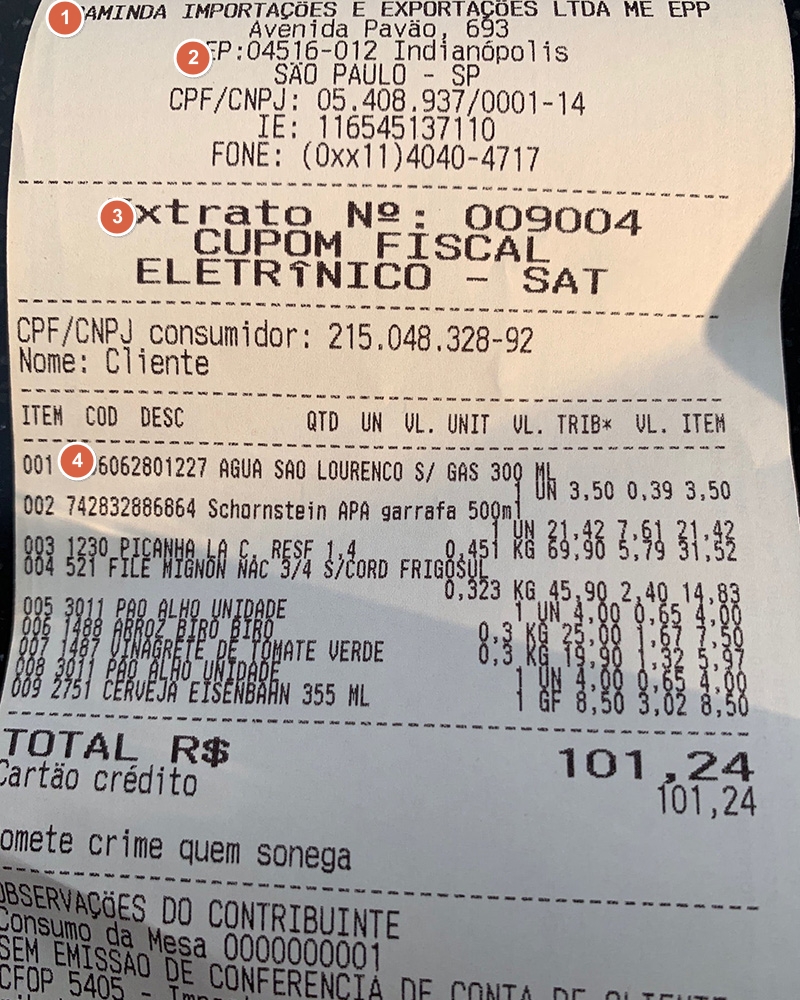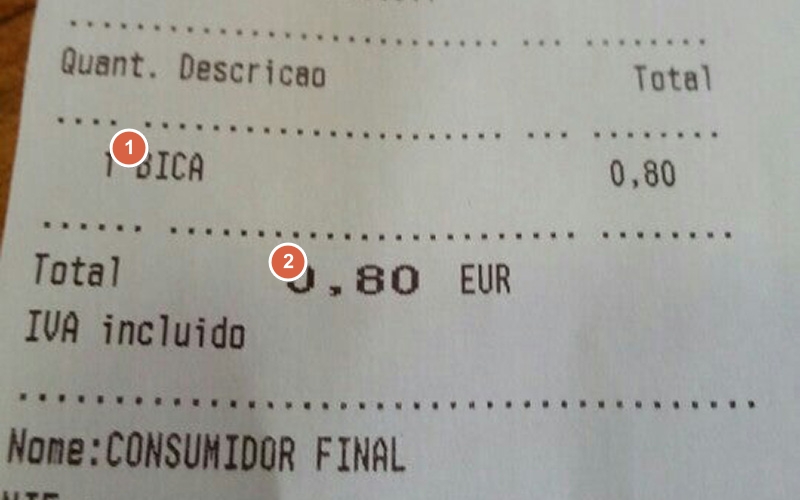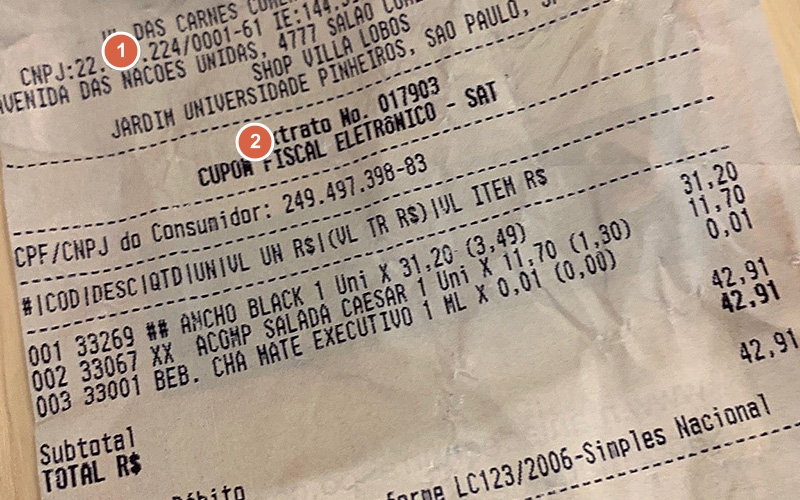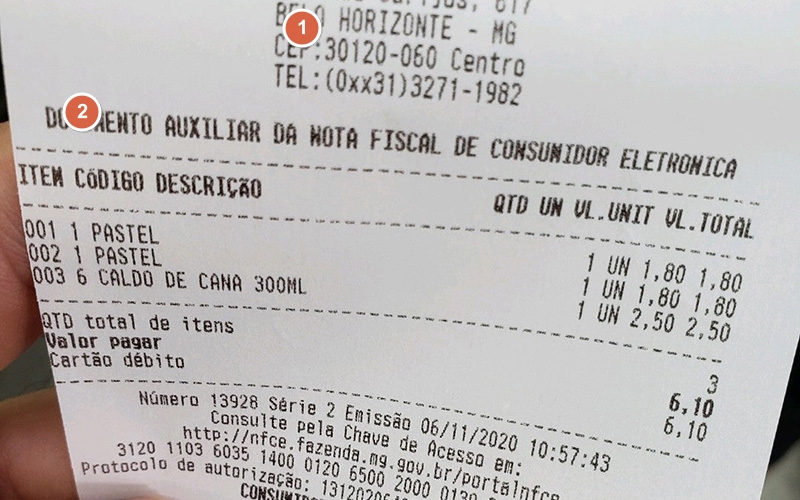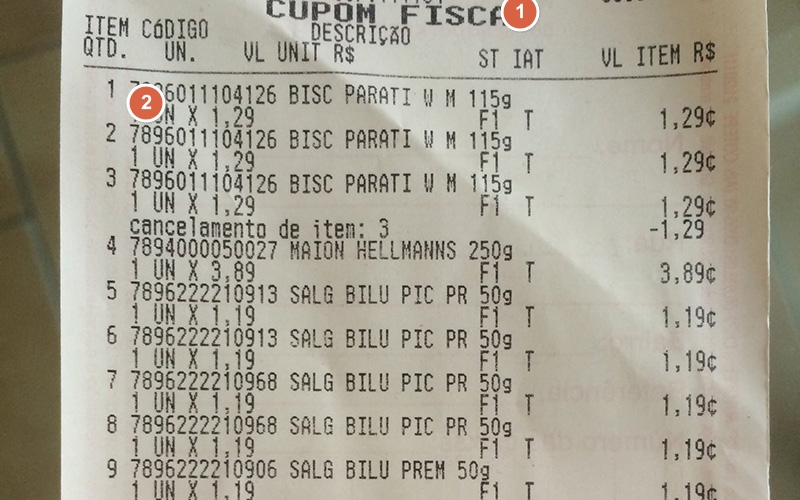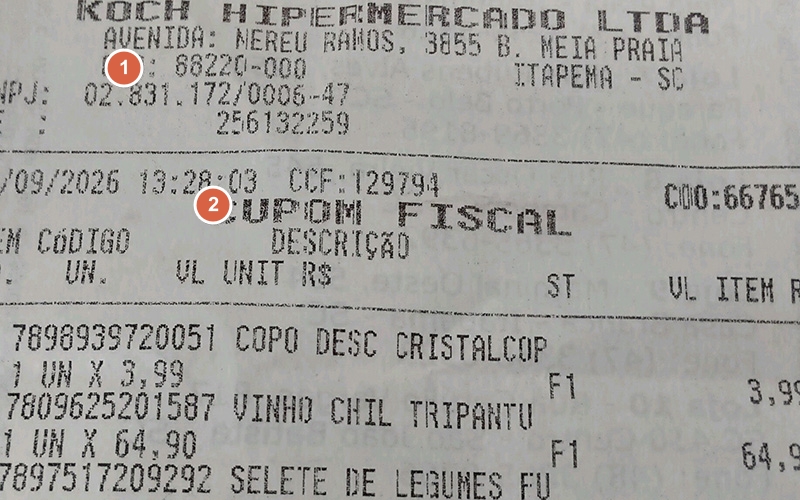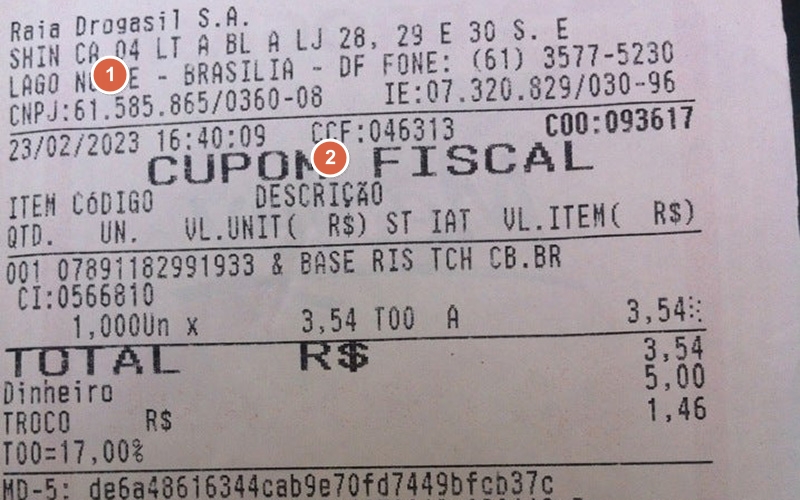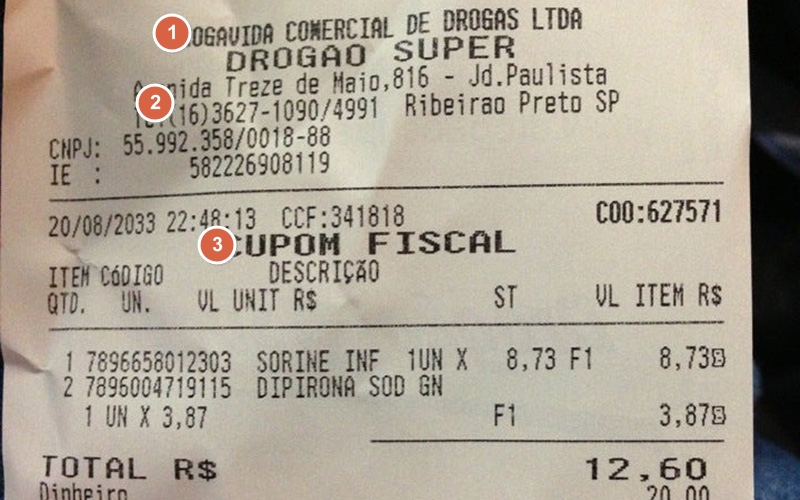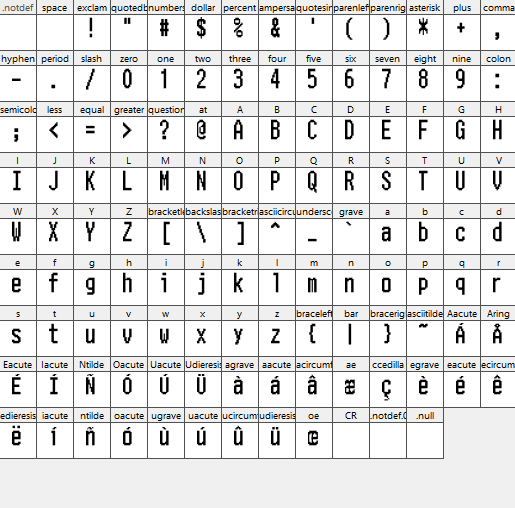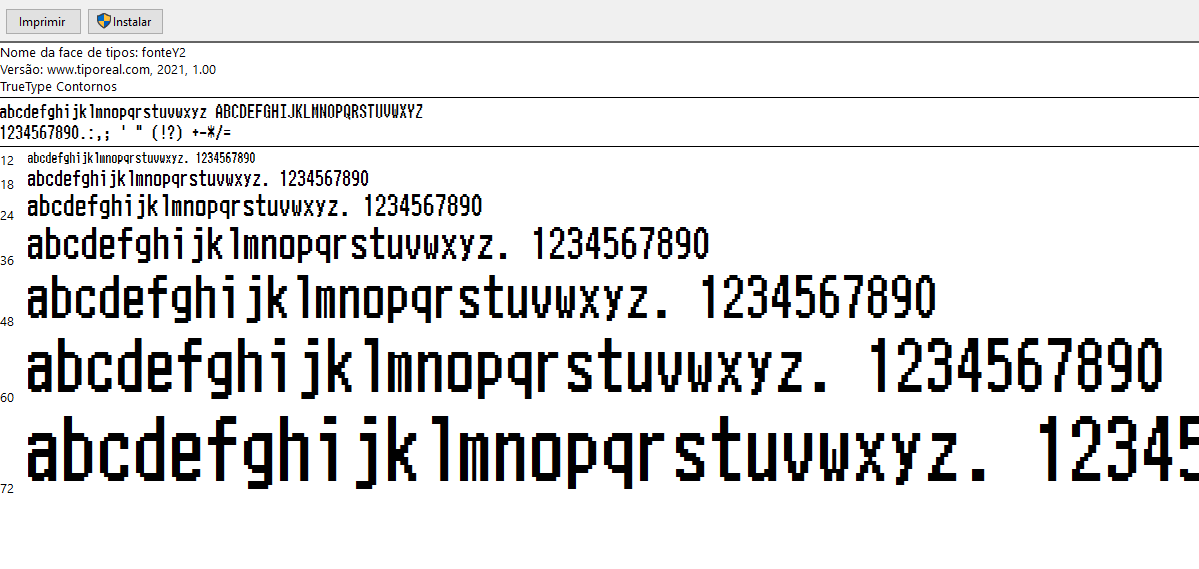
Amostra impressa da fonteY2 para nota fiscal de um restaurante em Brasil⤴
Amostra impressa da fonte para nota fiscal de um farmácia em Brasil⤴
Amostra impressa da fonte para cupom fiscal de um restaurante em Brasil (❶fonteZ2-negrito ❷fonteZ2 ❸fonteZ2-largo ❹fonteY2)⤴
Amostra impressa da fonte para nota fiscal de um restaurante em Brasil (❶fonteY2 ❷fonteZ2-negrito ❸fonteZ2)⤴
Amostra impressa da fonte para conta de um restaurante em Portugal (❶fonteY2 ❷fonteY2-largo)⤴
Amostra impressa da fonte para cupom fiscal de um restaurante em Brasil (❶fonteY2 ❷fonteY2-negrito)⤴
Amostra impressa da fonte para nota fiscal de um pastelaria em Brasil (❶fonteY2 ❷fonteY2-negrito)⤴
Amostra impressa da fonte para cupom fiscal de um supermercado em Brasil (❶fonteY2-negrito ❷fonteY2 ❸fonteY2-largo)⤴
Amostra impressa da fonte para cupom fiscal de um hipermercado em Brasil (❶fonteY2-largo ❷fonteY2)⤴
Amostra impressa da fonte para cupom fiscal de KOCH hipermercado em Brasil (❶fonteY2 ❷fonteY2-largo)⤴
Amostra impressa da fonte para cupom fiscal de um hamburgueria em Brasil (❶fonteY2 ❷fonteY2-largo)⤴
Amostra impressa da fonte para cupom fiscal de um farmácia em Brasil (❶fonteY2 ❷fonteY2-largo)⤴
Amostra impressa da fonte para cupom fiscal de um farmácia em Brasil (❶fonteY2-negrito ❷fonteY2 ❸fonteY2-largo)⤴
Todos os personagens⤴
O que parece quando aberto com o visualizador de fontes padrão do Windows⤴